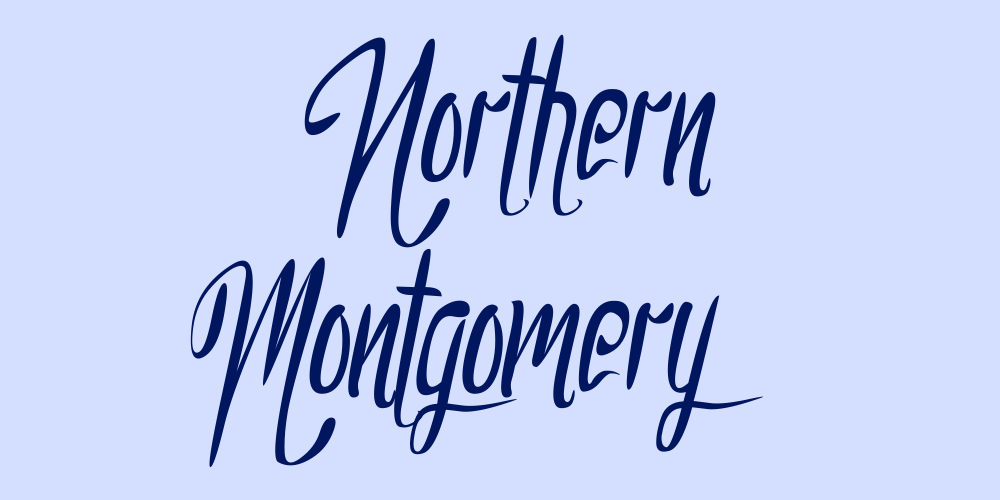
A Northern Montgomery é uma linda fonte script que traz ao seu design editor a oportunidade de criar textos vívidos e agradáveis para qualquer projeto editorial. Seu traçado fluido e expressivo consegue capturar as nuances das letras, tornando-se especialmente adequada para aplicativos como cartazes, anúncios digitais ou até mesmo para personalizar mensagens no formato digital. A Hamilton desenvolveu esta fonte, dedicando-se à criação de detalhes sutis e características únicas que dão vida a qualquer texto que você escrever. Com uma paleta vibrante e um desempenho fluido em dispositivos modernos, é perfeita para projetos que exigem tanto personalidade quanto elegância. Download agora e deixe sua escrita soar tão única quanto você!